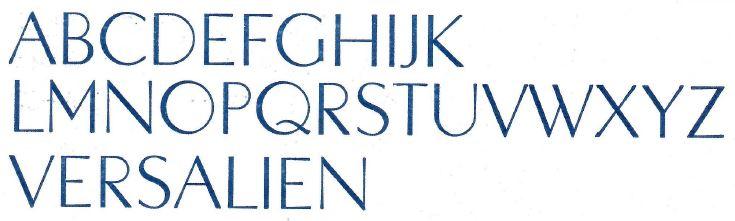
Bleischrift identifizieren
ich versuche, die anhängende Bleischrift zu identifizieren. Leider habe ich keine weiteren Informationen zu dieser Schrift. Die Schrift stammt aus einem Druckereibestand, in dem sich Vertreter aller größeren Gießereien bis in die 1950er befanden.
Es sind nur Versalien vorhanden, ich weiß jedoch nicht, ob es nicht doch Gemeine dazu gibt.
Gelöst von Erwin Krump
Diese Schrift ist mir unter dem Namen „Florida“ bekannt. W. Woellmers Schriftgießerei, Berlin, 1931.